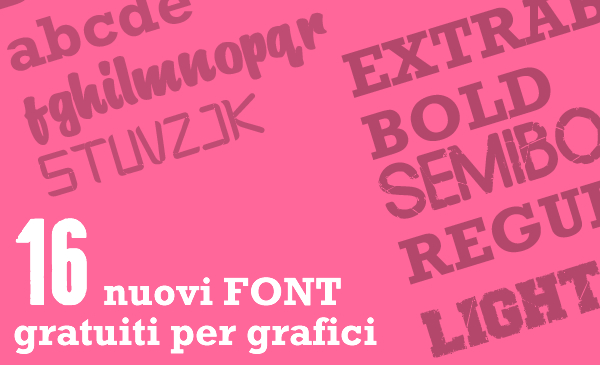
Se alla vostra collezione di font mancano quelli in stile sans serif disegnati a mano, vi consiglio di dare un'occhiata alla collezione del sito Graphic Design Junction.
La raccolta è composta da 16 font gratuiti di alta qualità perfetti per logotipi, marchi e qualsiasi tipo di grafica tipografica che possono rendere qualsiasi design più professionale.
16 nuovi font gratuiti per grafici